「カワイイ文字も正義!」キュートなデザインをさらにかわいくする、かわいらしい書体・フォントを厳選してみた
「カワイイは正義!」であるように、「カワイイ文字も正義!」で間違いないだろう。
そこで、かわいいデザインをさらにかわいくする、かわいい形の書体を厳選してみた。
少女マンガ系カワイイ文字「優雅宋」
ストロークの先端と末端に欧文書体の花文字のような装飾が施されているのが特徴で、少女マンガやガーリーなファッションなどにぴったりの文字
ゆるいかわいらしさのある文字「てがき楽」
カワイらしさが表現された手書き風書体。
かわいい商品包装、雑誌のサブタイトル、マンガの吹き出しなどにおススメ。
女子校生のまる文字「まるもじ体」
女子中高生が手書きしたような、まる文字。
明るくかわいらしい印象で、女性や子供向けのデザインに適している。
子供の遊び心を感じる「クラフト遊」
こどもが書いた文字のような短い点や線で構成された書体。
ほっこりかわいい文字「クラフト墨」
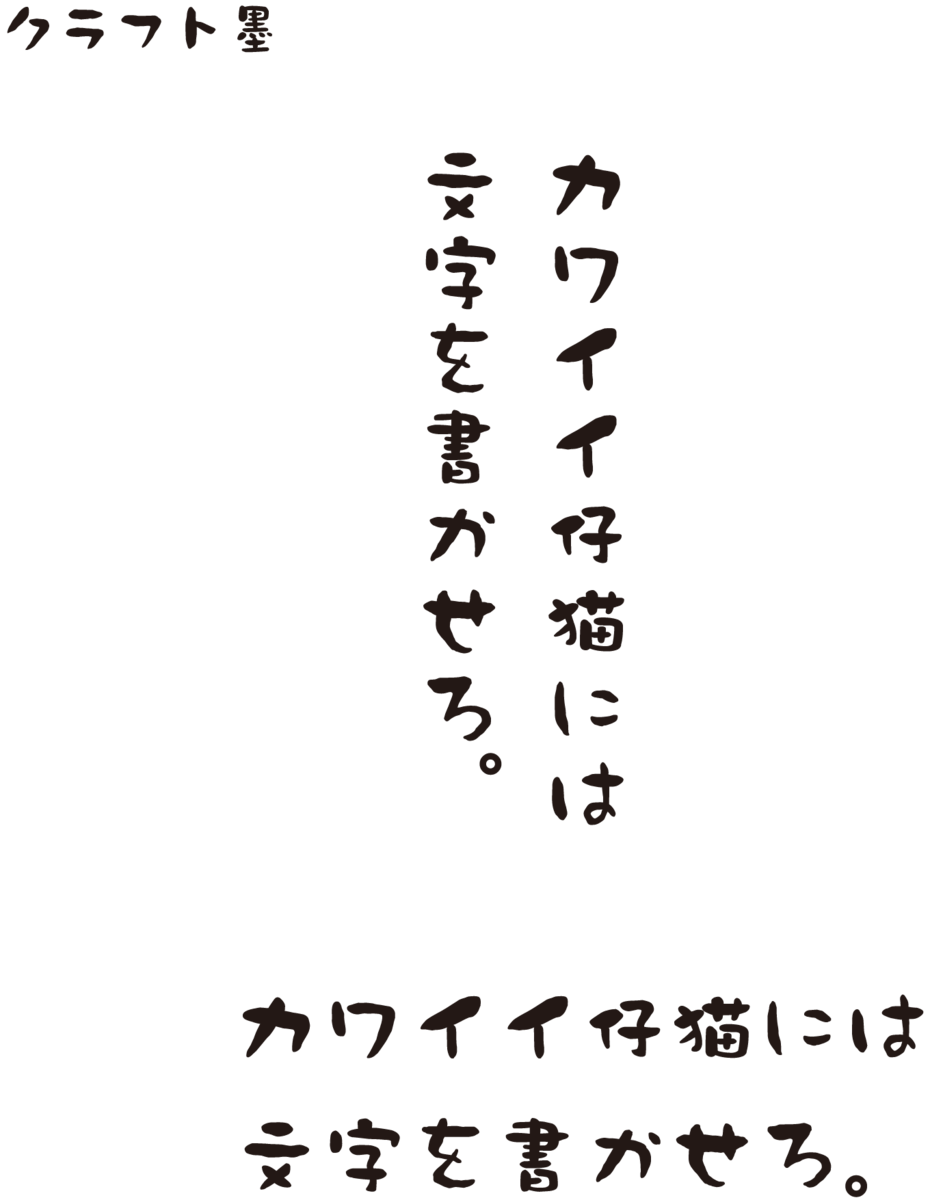
なんだかほっこりさせる丸っこい墨文字のフォント。
ゆるキャラやテロップに使用される率も高い脱力系書体。